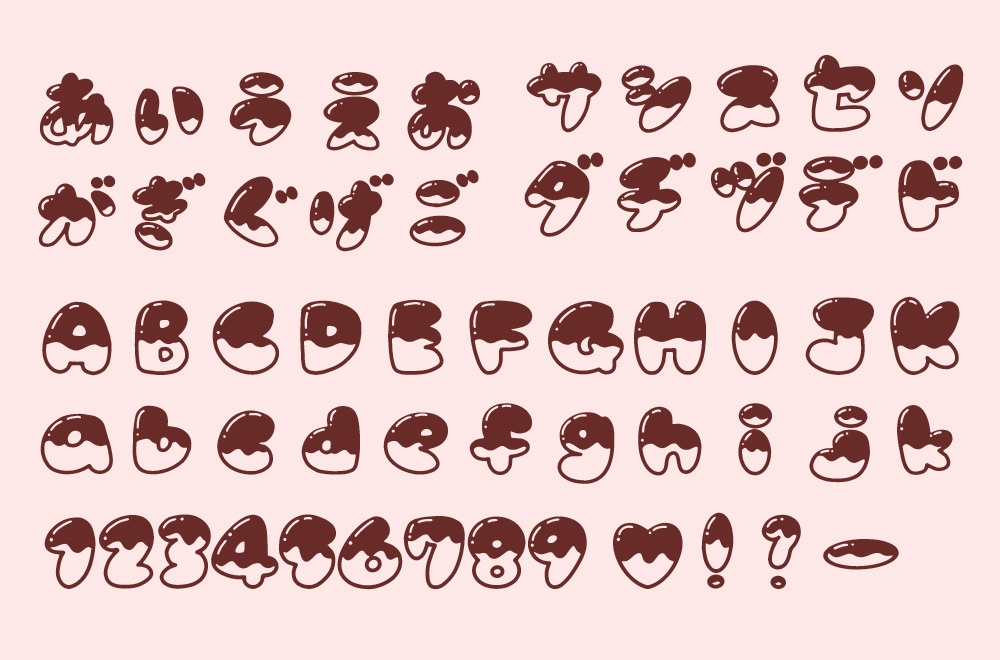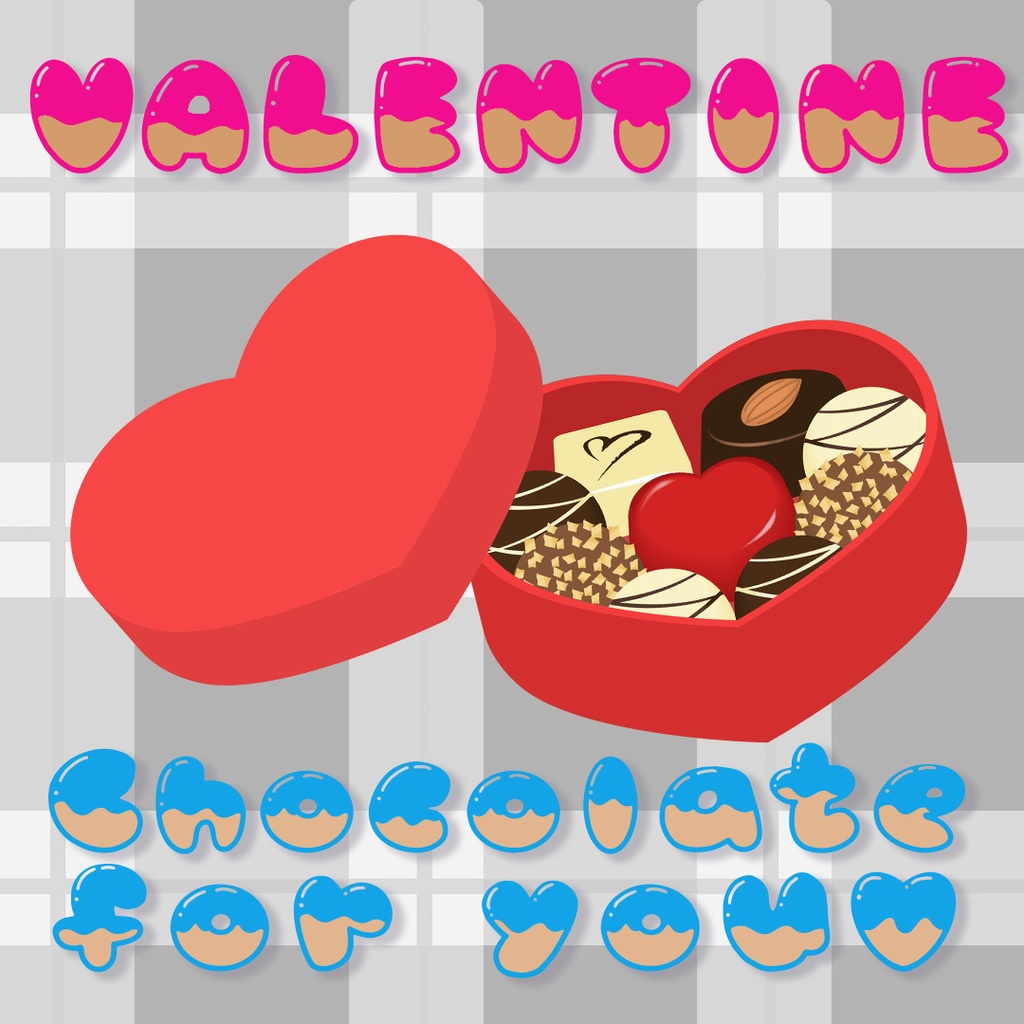
手書きフォントまるチョコ
まるチョコは、手書きのまるい文字にチョコレートがかかったような見た目の美味しそうなフォントです。 フリー版はひらがなのみ、有料版はひらがな、カタカナ、アルファベット、数字と一部記号を収録しています。句読点の「。」を入力するとハートになります。 <使い方> そのままで使っても、中抜きの所に好きな色を入れるなどしてよりお菓子感を出したりしても楽しめるフォントです。 <フォント形式> OpenType < 動作環境>Mac OSシステムでの動作確認済みです。 Windowsはフリー版で動作確認していただけますと幸いです。 <ご利用規約> *こちらのフォントは個人利用、商用利用(印刷物・ゲーム・アプリ・映像・動画・ロゴ・同人作品など)問わずにお使いいただけるフォントです。文字の加工や変更も可能です。 *このフォントの著作権は放棄しておりますん。フォントファイルを二次加工・再配布・再販売などは禁止しております。 *当フォントを使用した際に発生した機器およびソフトウエアの故障、誤動作、誤出力、ウイルスへの感染などに関して責任を負わないものとします。 本ファイルは武蔵システム(http://opentype.jp/)の(OTEdit for Mac)を使い作成しました。